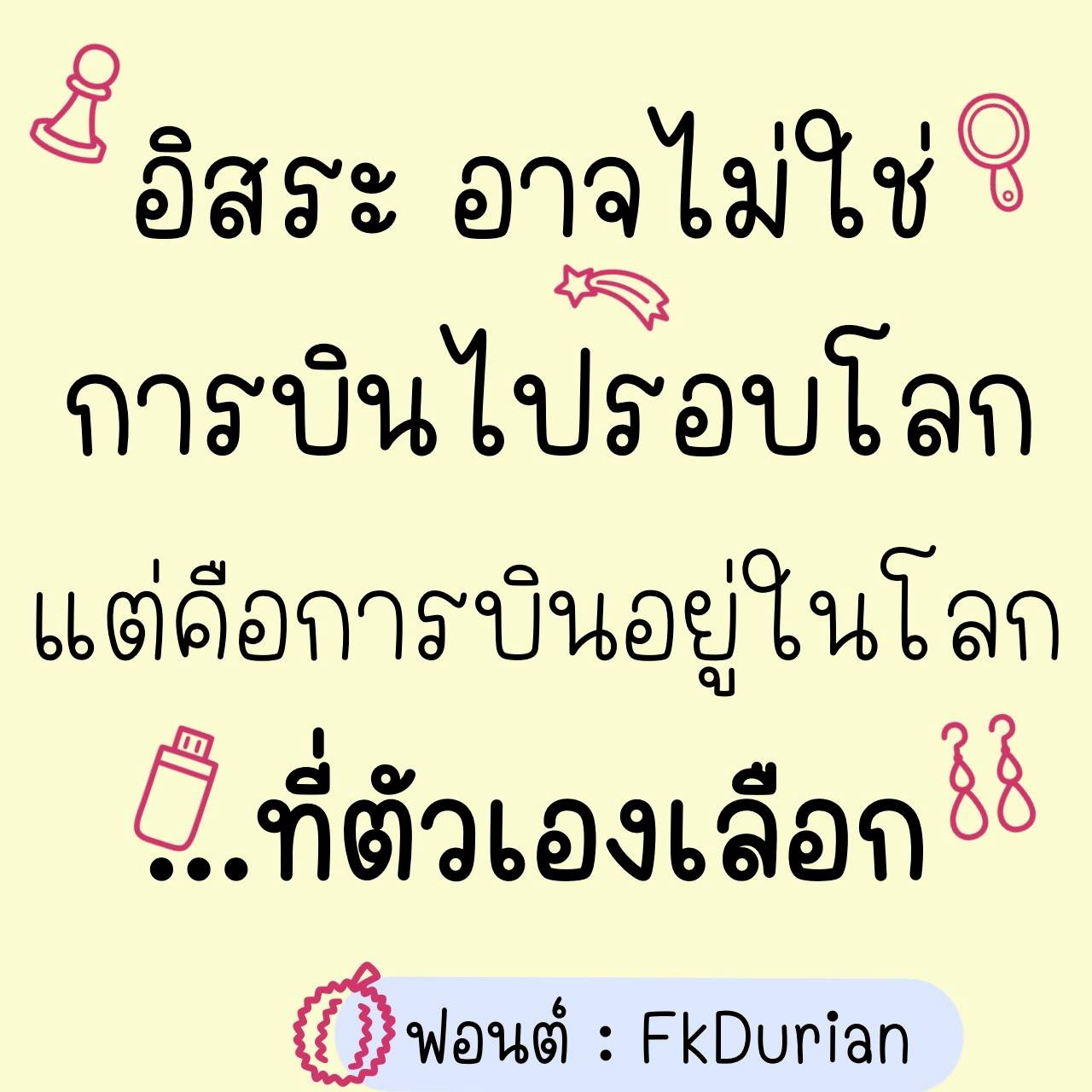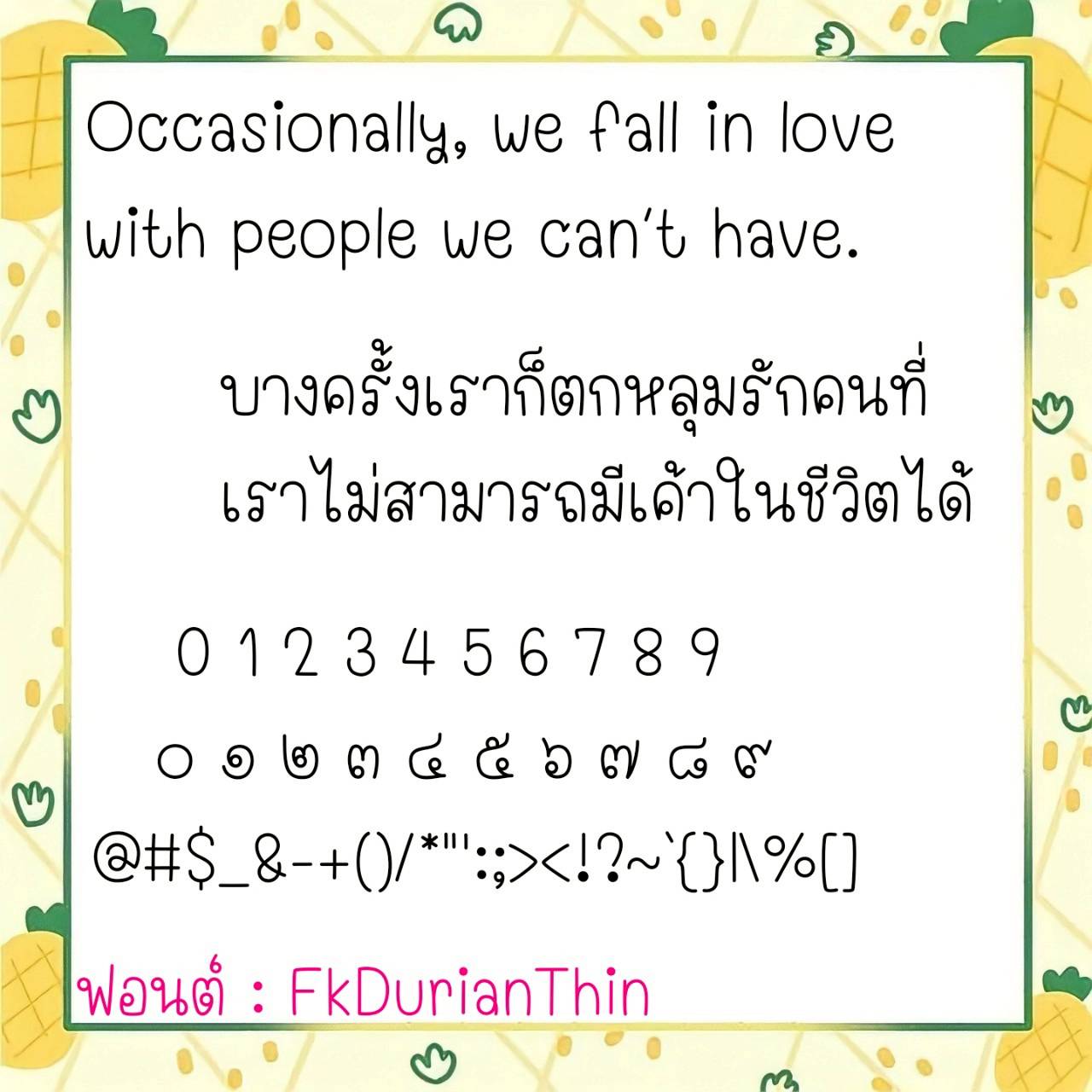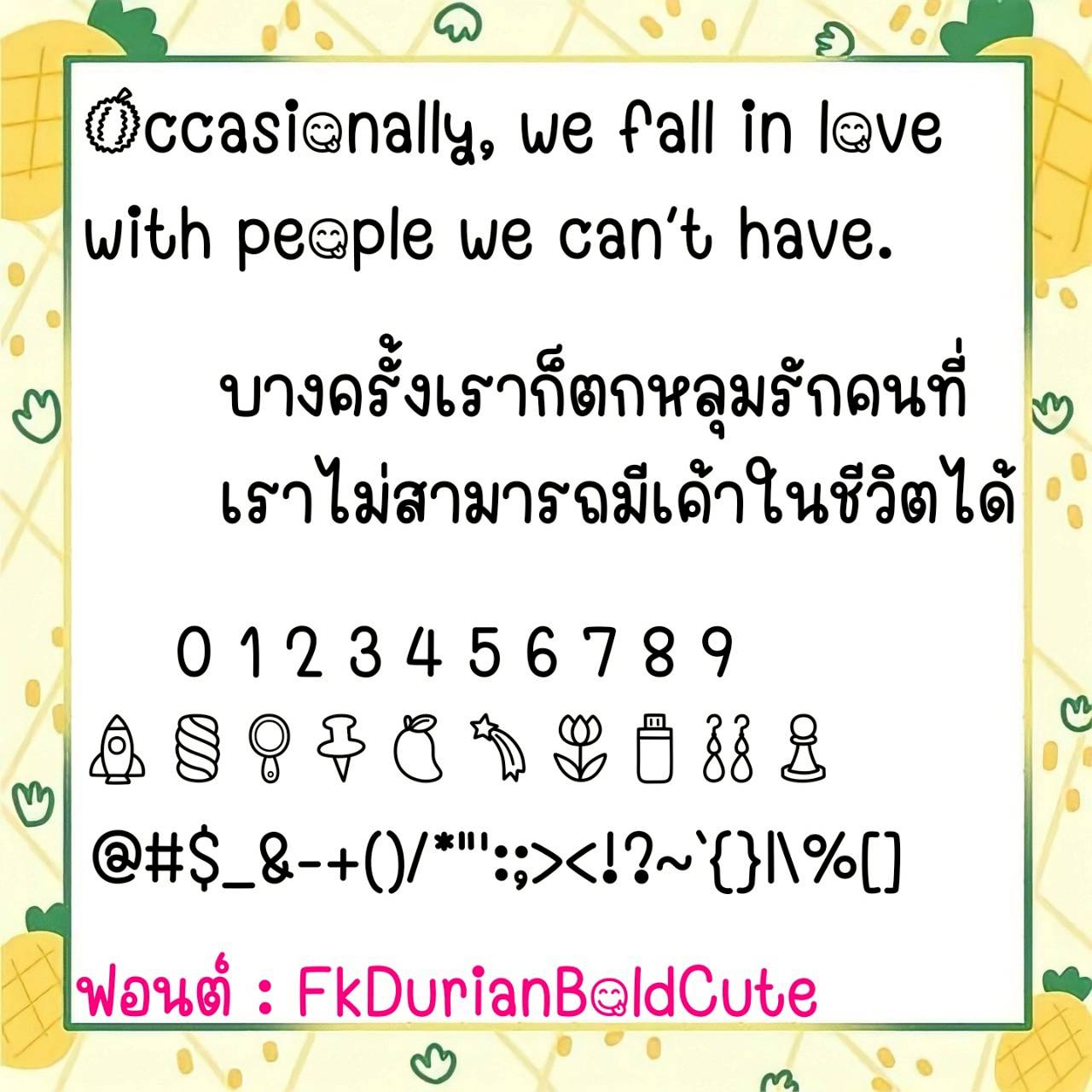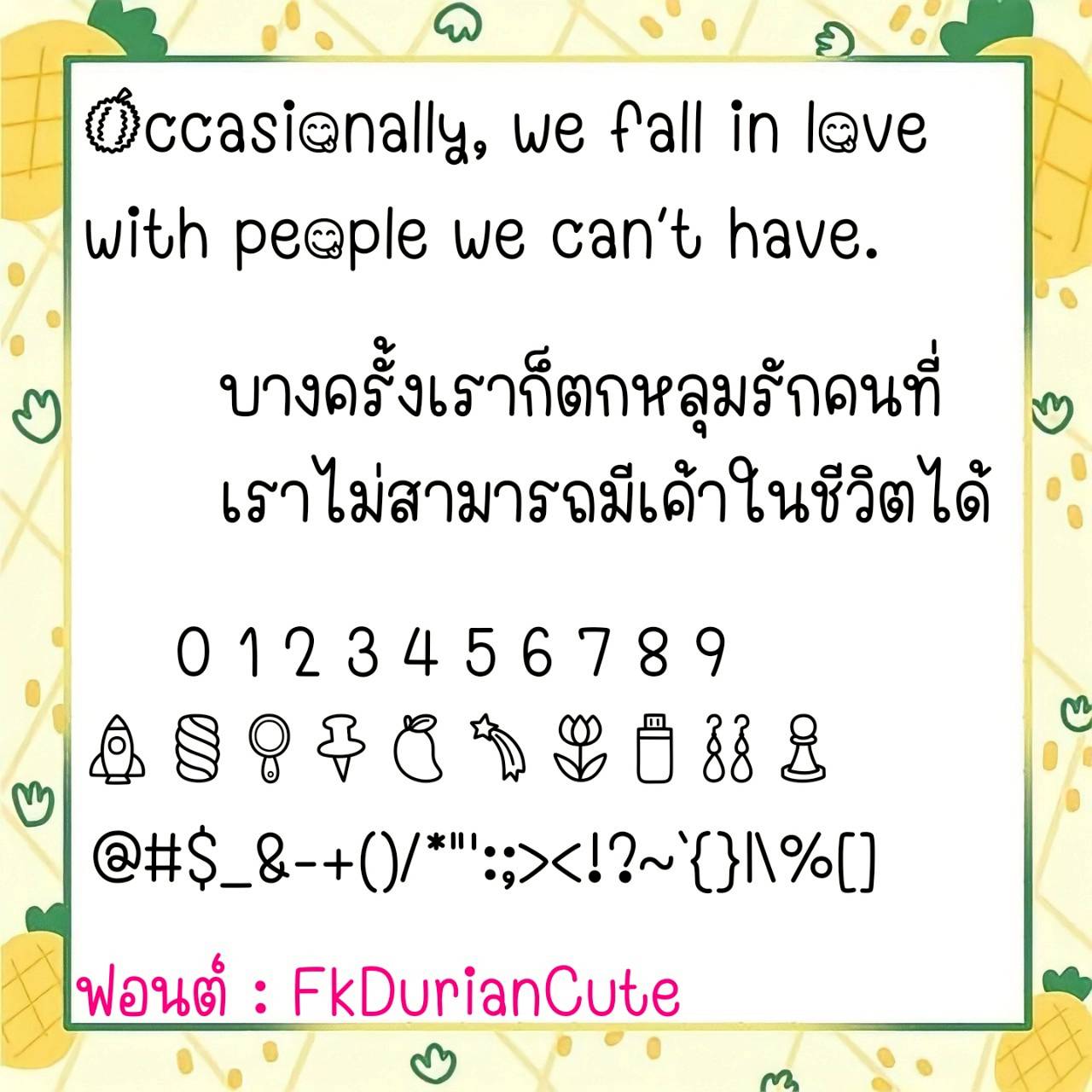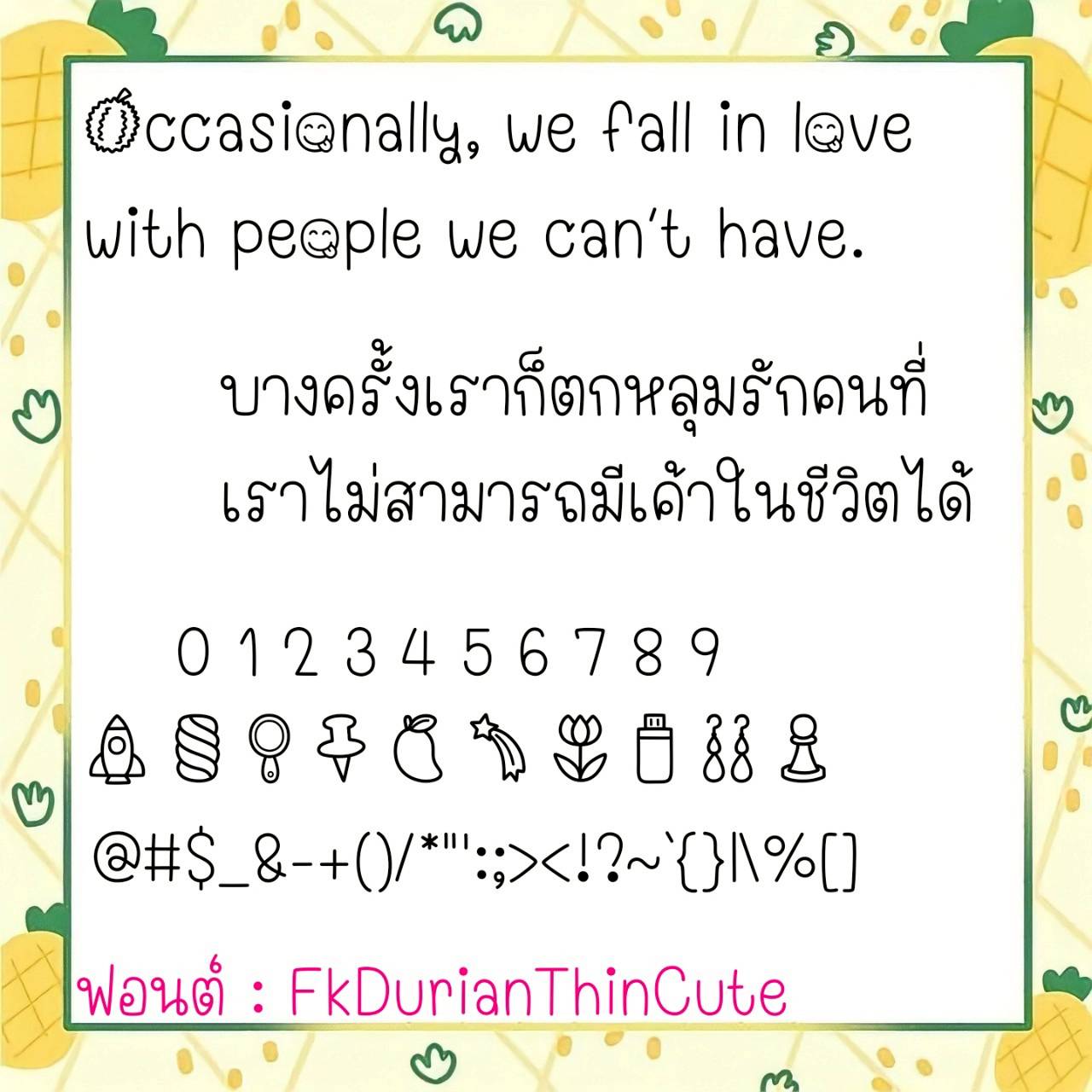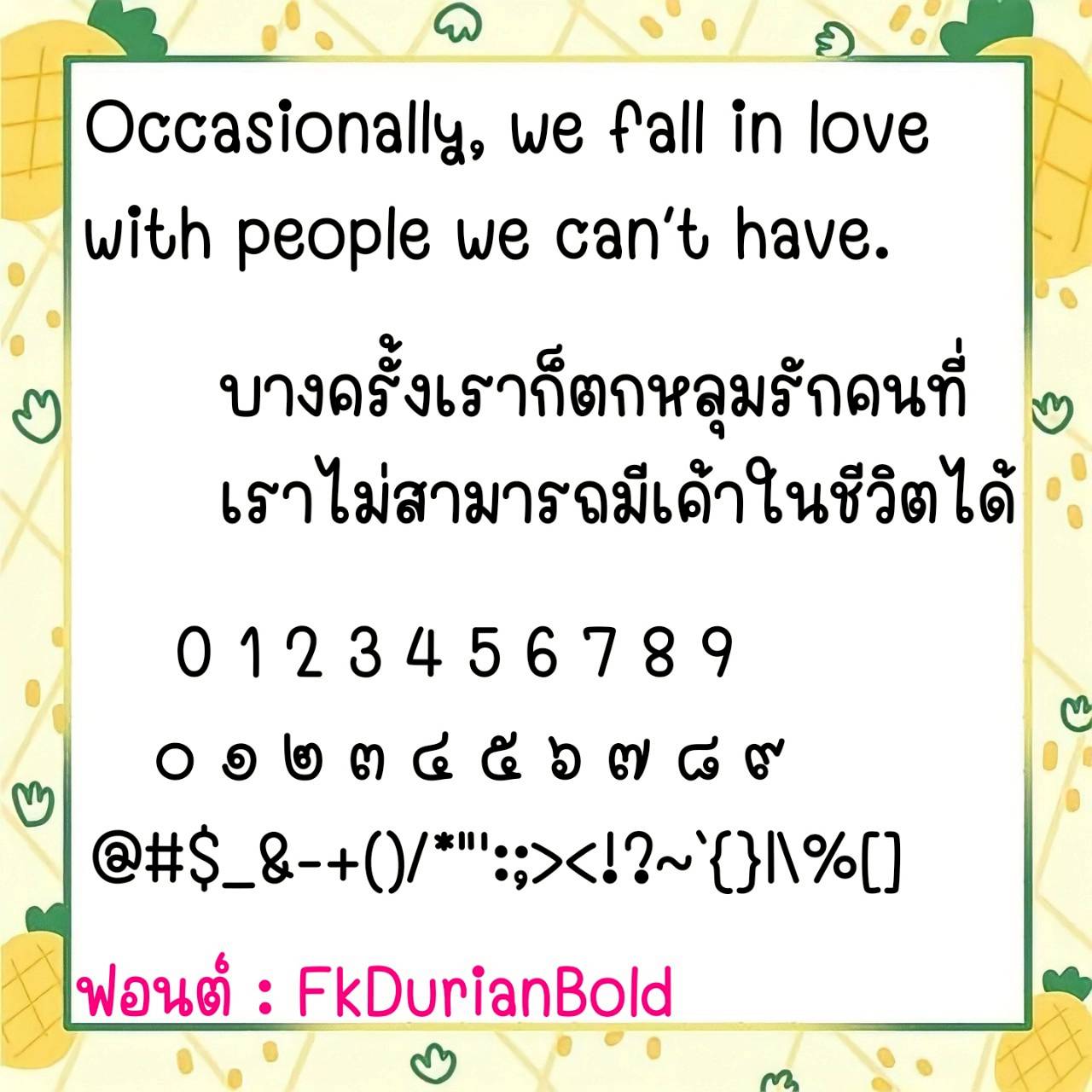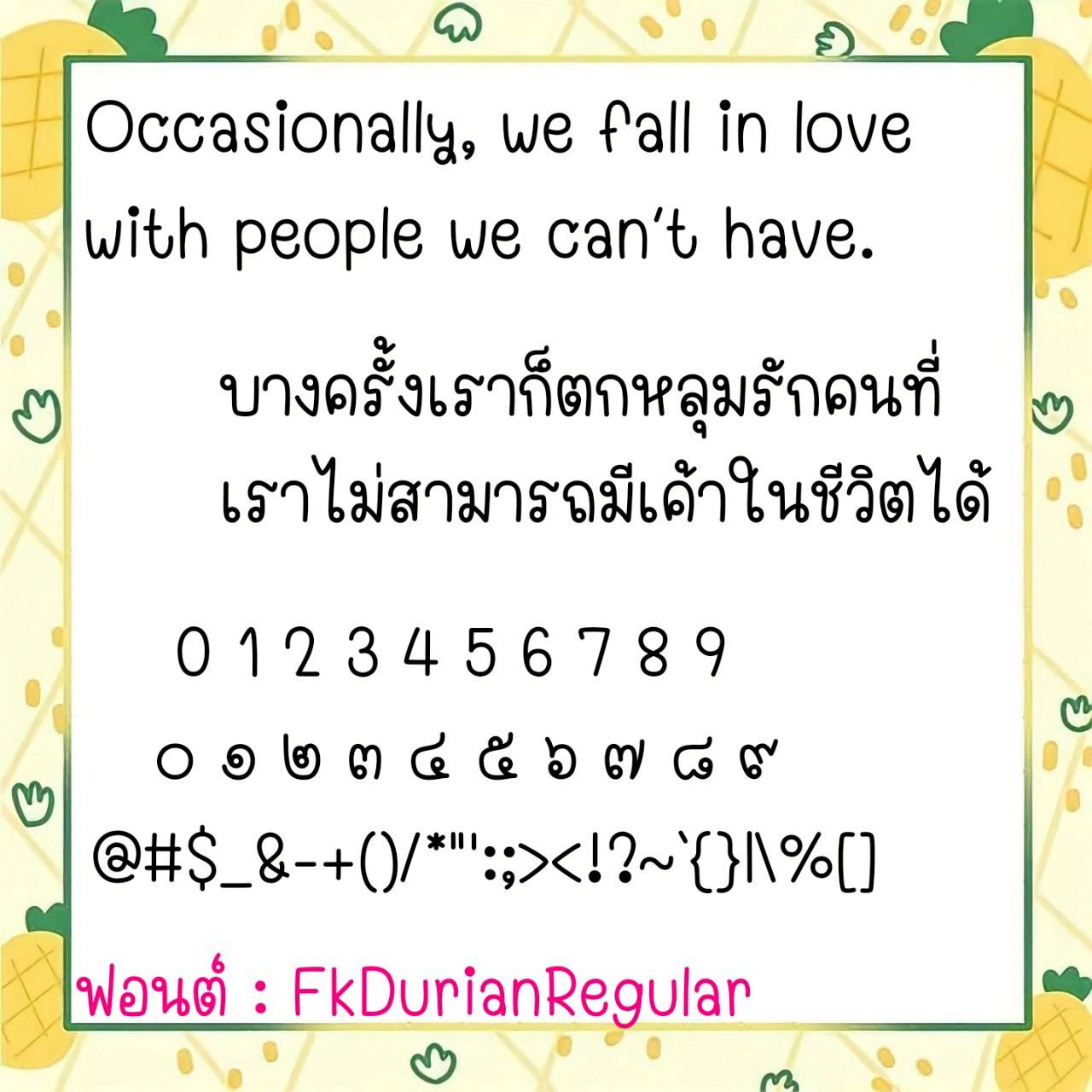
Font FkDurian
🔸 ฟอนต์ลายมือขนาดตัวพอดีๆ ดูมีความน่ารักแบบวัยรุ่นในตัว ใช้งานได้หลากหลาย ดูสบายตาไม่น่าเบื่อ และยังมีไฟล์อิโมจิน่ารักๆ ที่ใช้แทนเลขไทยให้ด้วยค่ะ 🥰💙
🔹 Handwritten fonts with a moderate size look cute and youthful. They can be used in many ways, are easy on the eyes, and are not boring. There are also cute emoji files that can be used to replace Thai numerals. 🥰💙